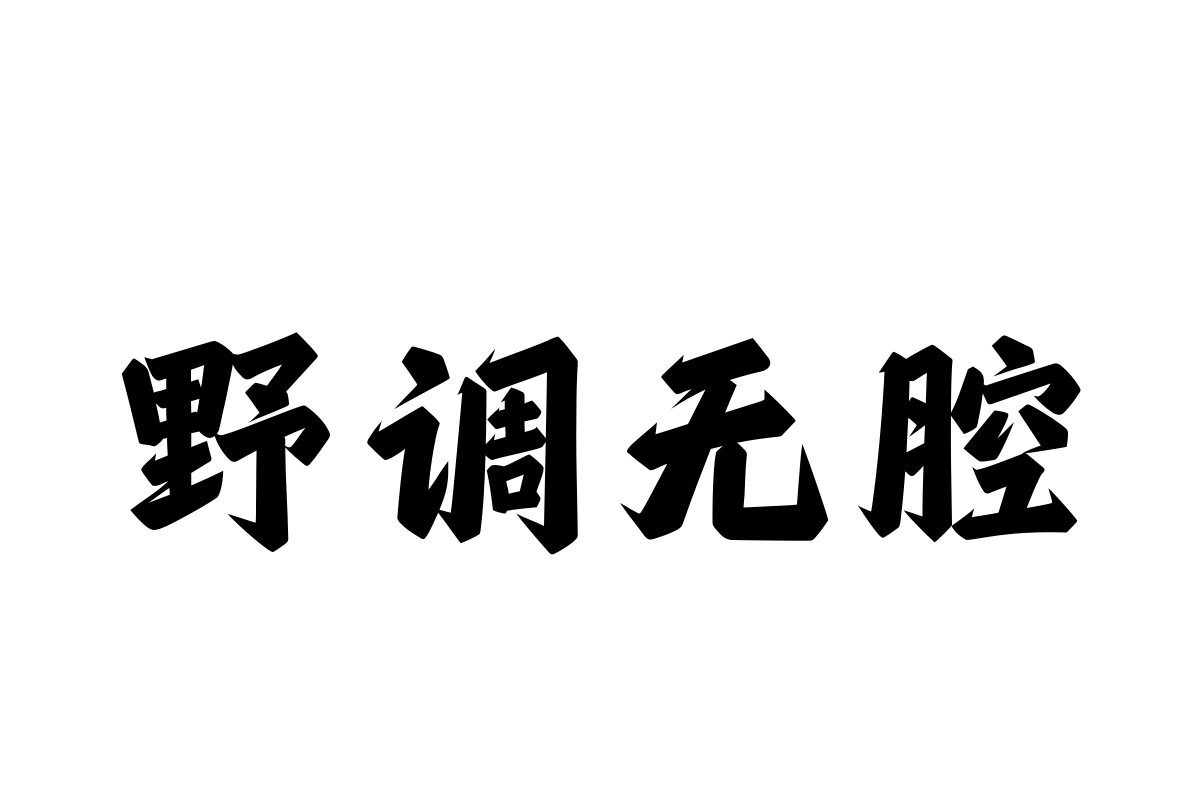
汉仪风波龙是一套具有现代感和动感的中文字体,由汉仪字库出品。这套字体设计灵感来源于中国传统书法中的“龙”元素,通过独特的笔画结构和风格,展现出一种强烈的视觉冲击力和艺术美感。
汉仪风波龙的特点如下:
1. 笔画流畅:这套字体的笔画线条流畅自然,没有过多的装饰性细节,使得整体看起来更加简洁大方。
2. 结构紧凑:每个字符的间距和空间都经过精心设计,使得整个字体结构紧凑有序,易于阅读和识别。
3. 风格独特:汉仪风波龙在保持传统中文书写美感的同时,融入了现代设计元素,使得整个字体既有古典韵味,又不失时尚感。
4. 适应性强:这套字体适用于各种印刷媒介,包括报纸、杂志、书籍、广告等,能够满足不同场景的需求。
总之,汉仪风波龙是一款极具个性和创意的中文字体,适合用于需要突出个性和艺术氛围的设计项目。